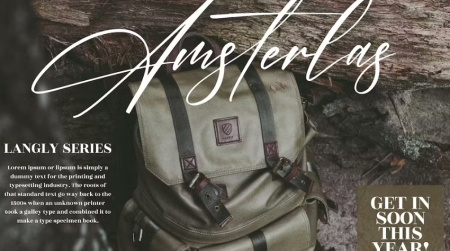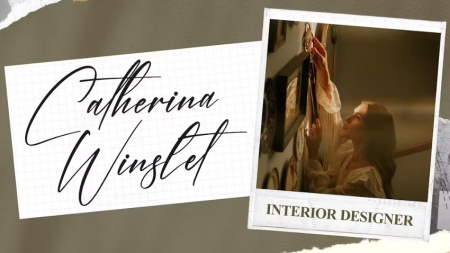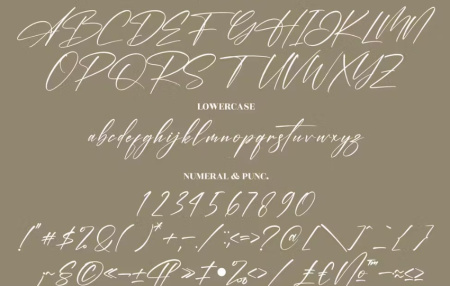
دانلود فونت انگلیسی آمستردام Amsterdam Signature
دانلود فونت انگلیسی آمستردام Amsterdam Signature. فونت انگلیسی امضای آمستردام شامل مجموعه ای از حروف و اعداد مناسب انواع پروژه های شما، تکمیل محصولات خلاقانه دیجیتال و چاپی شما مناسب است. این فونت برای پوسترها، پست های رسانه های اجتماعی، برندسازی، پروژه های شخصی و غیره مناسب است. این فونت دست نویس آمستردام مناسب برای طراحی و انواع گرافیک ها مناسب است. برای مشاهده تصاویر این فونت زیبا در ادامه مطلب از سایت gfx با ما همراه باشید.
فونت انگلیسی امضای آمستردام Amsterdam Signature
فونت دست نویس آمستردام Amsterdam Signature
فونت انگلیسی آمستردام Amsterdam Signature
دانلود فونت انگلیسی امضای آمستردام Amsterdam Signature